숫자 폰트 찾아주세요
Tablet Gothic Condensed 아닙니다. 미세하게 다른 것 같습니다.
Tablet Gothic Condensed 폰트가 아닌 이유..
1. 1의 시작부분이 수직으로 떨어진다.
2. 2의 시작부분이 바닥과 평행이다.
3. 7도 Tablet Gothic Condensed 폰트와는 다르게 둥근 부분이 없습니다.
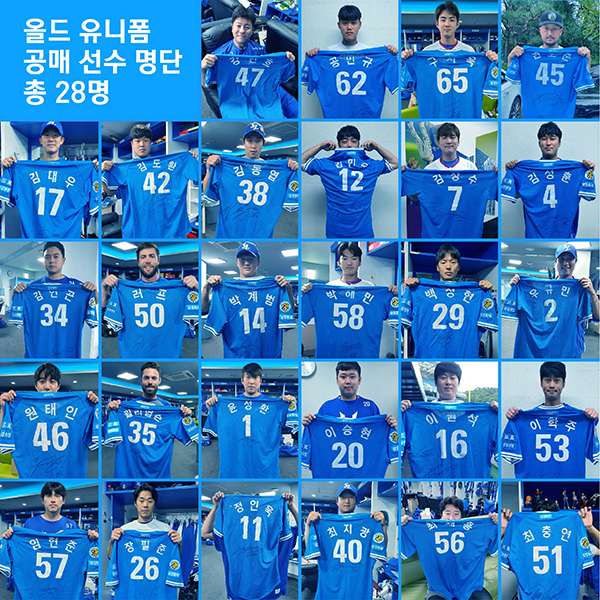
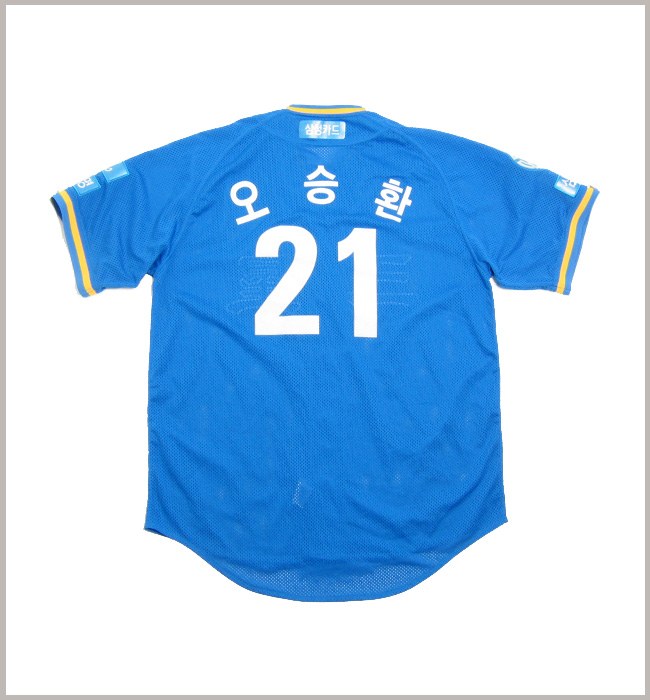
구단 폰트일수도 있습니다~
Univers 폰트의 Bold Condensed 웨이트랑 가장 비슷해 보입니다(기본폰트)